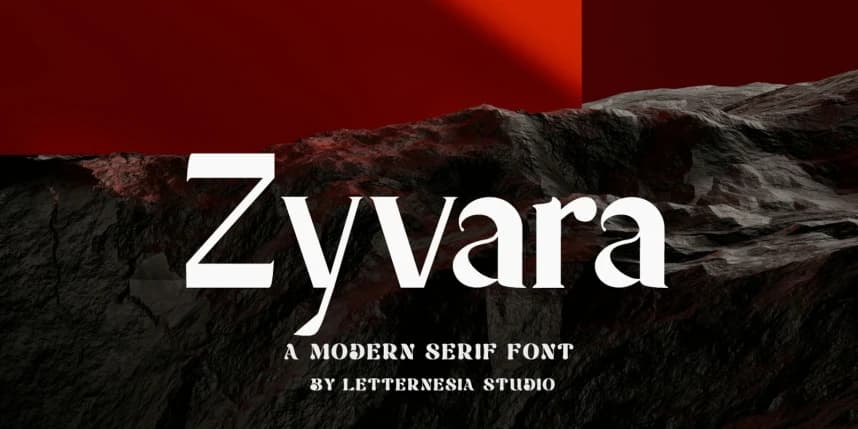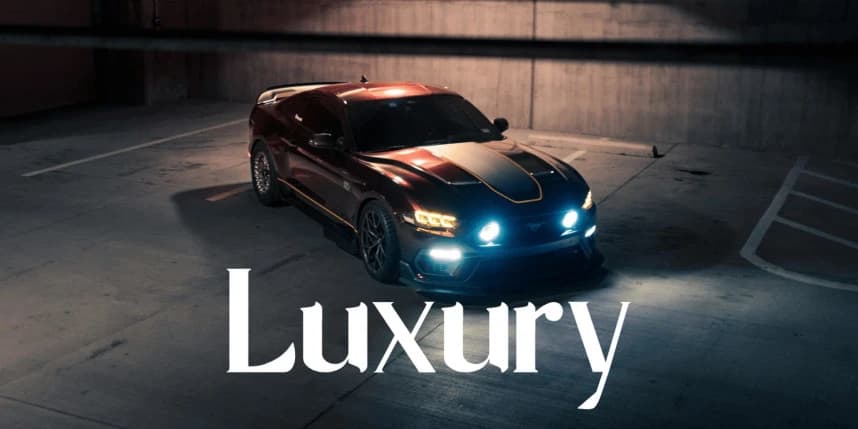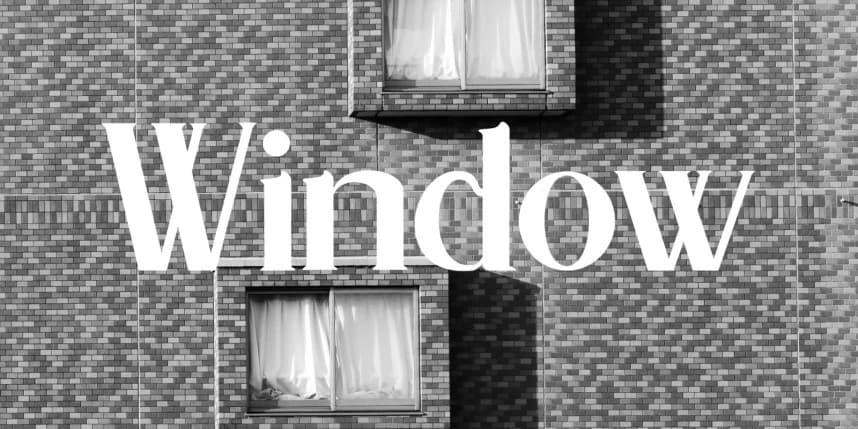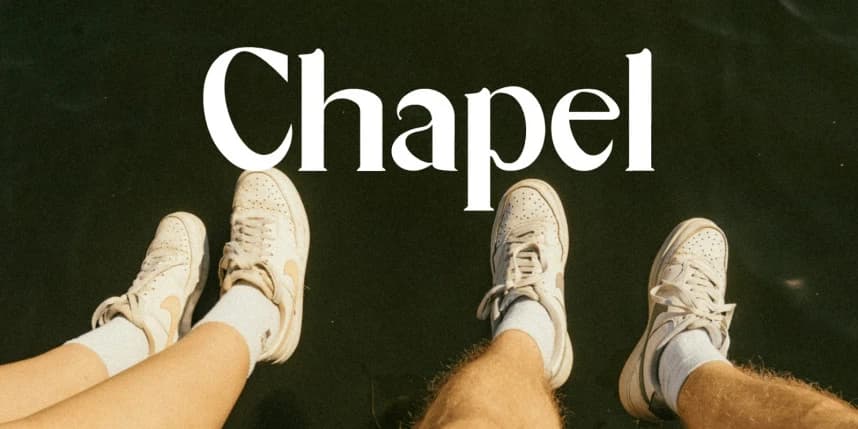
Zyvara Font
Zyvara Font display modern yang dirancang untuk membuat setiap desain terlihat lebih berkelas dan menonjol. Dengan proporsi tegas, lekukan elegan, dan detail rapi, Zyvara menghadirkan kesan profesional sekaligus kreatif.